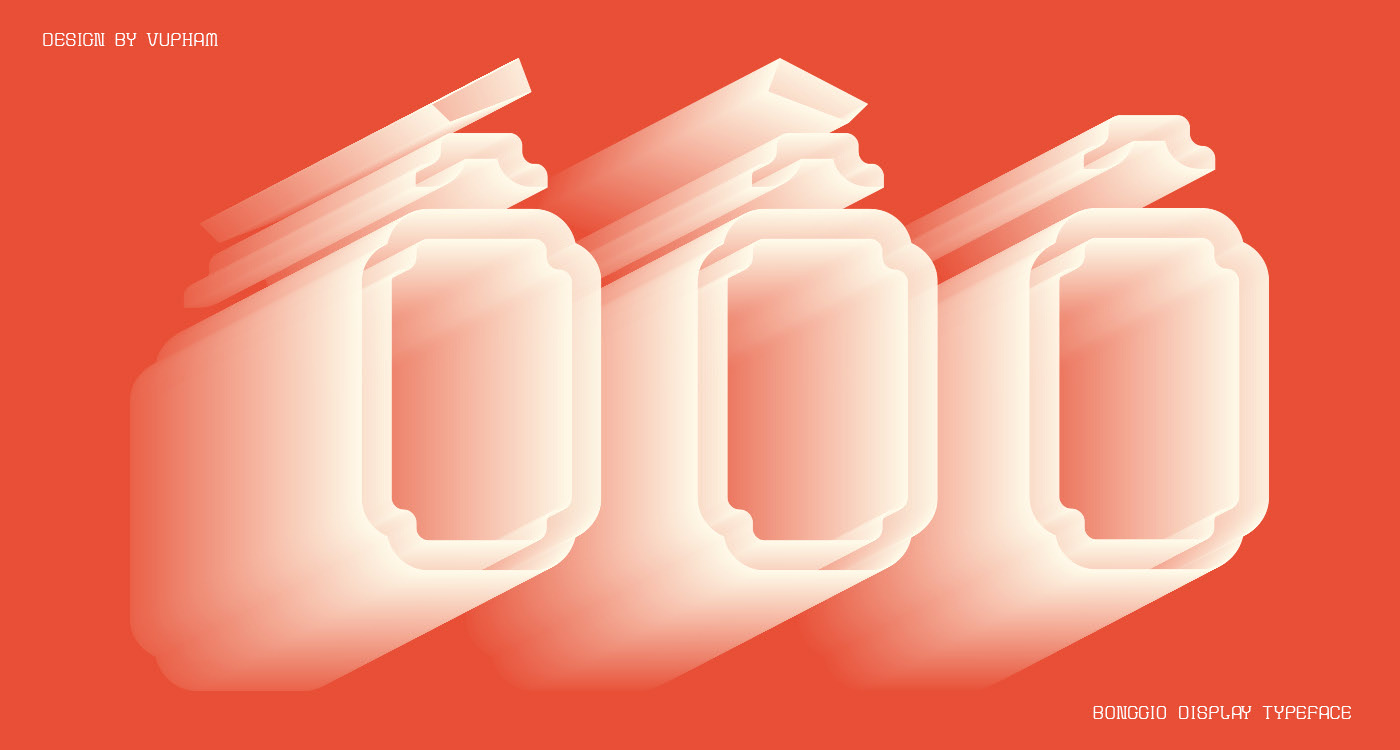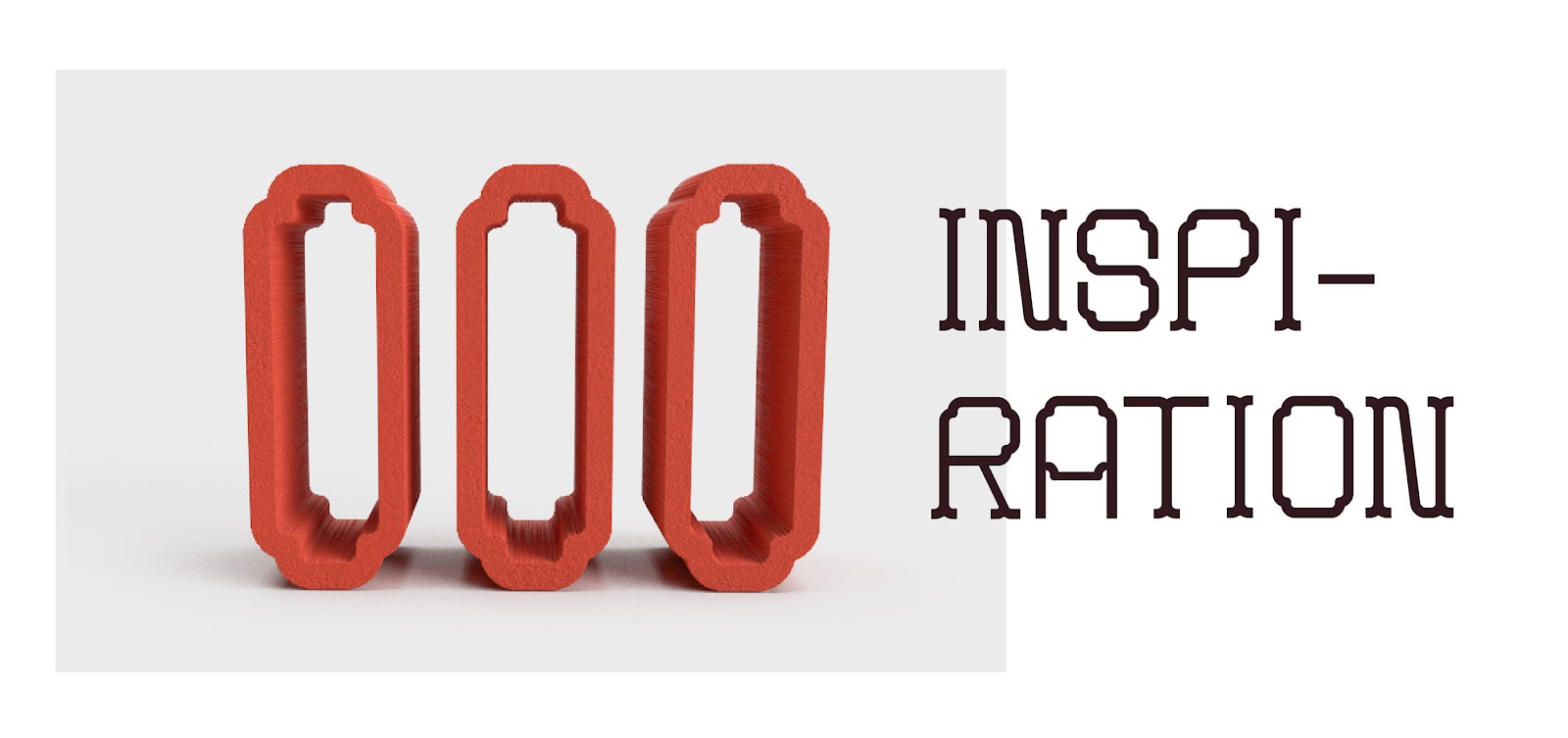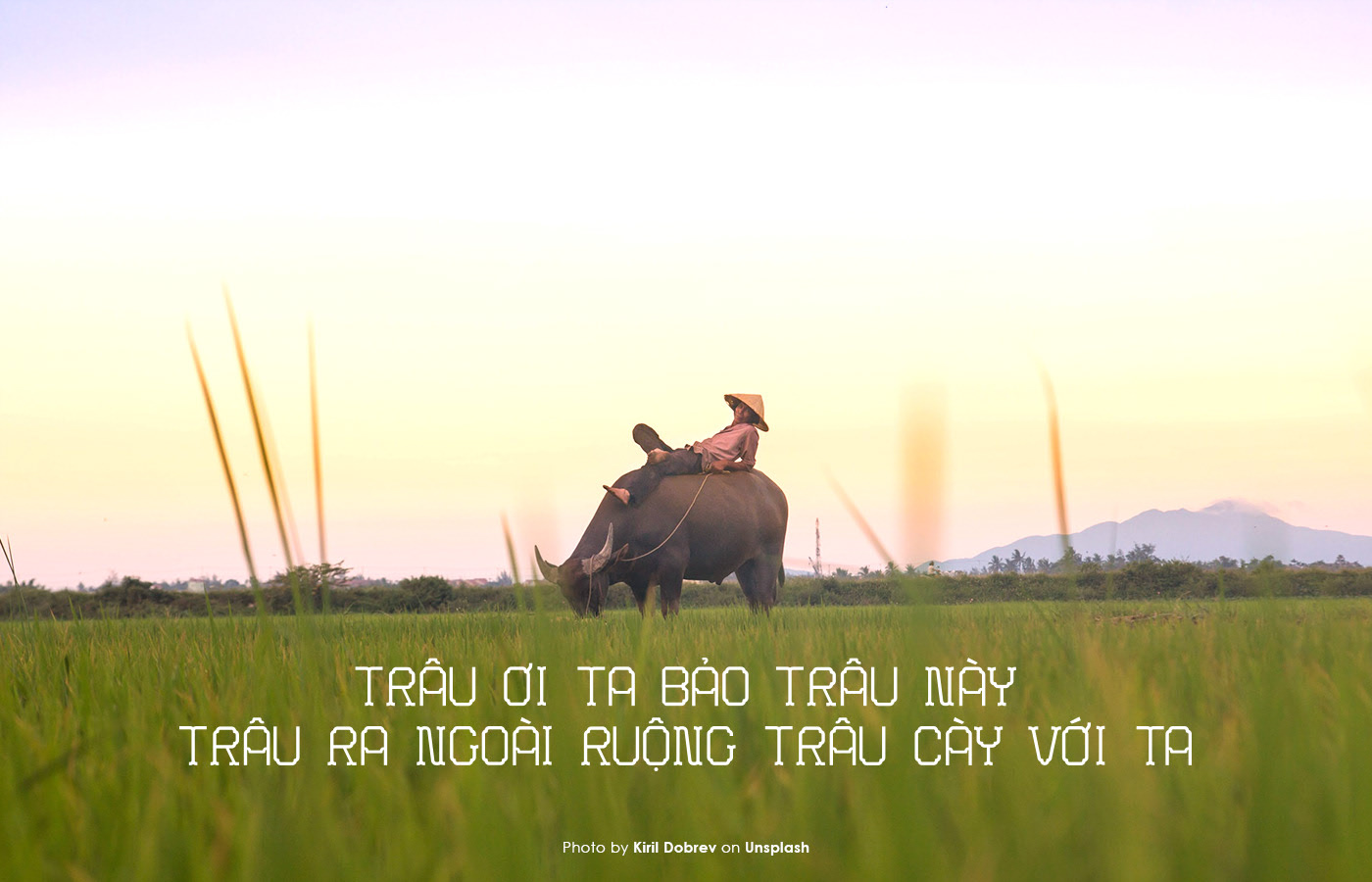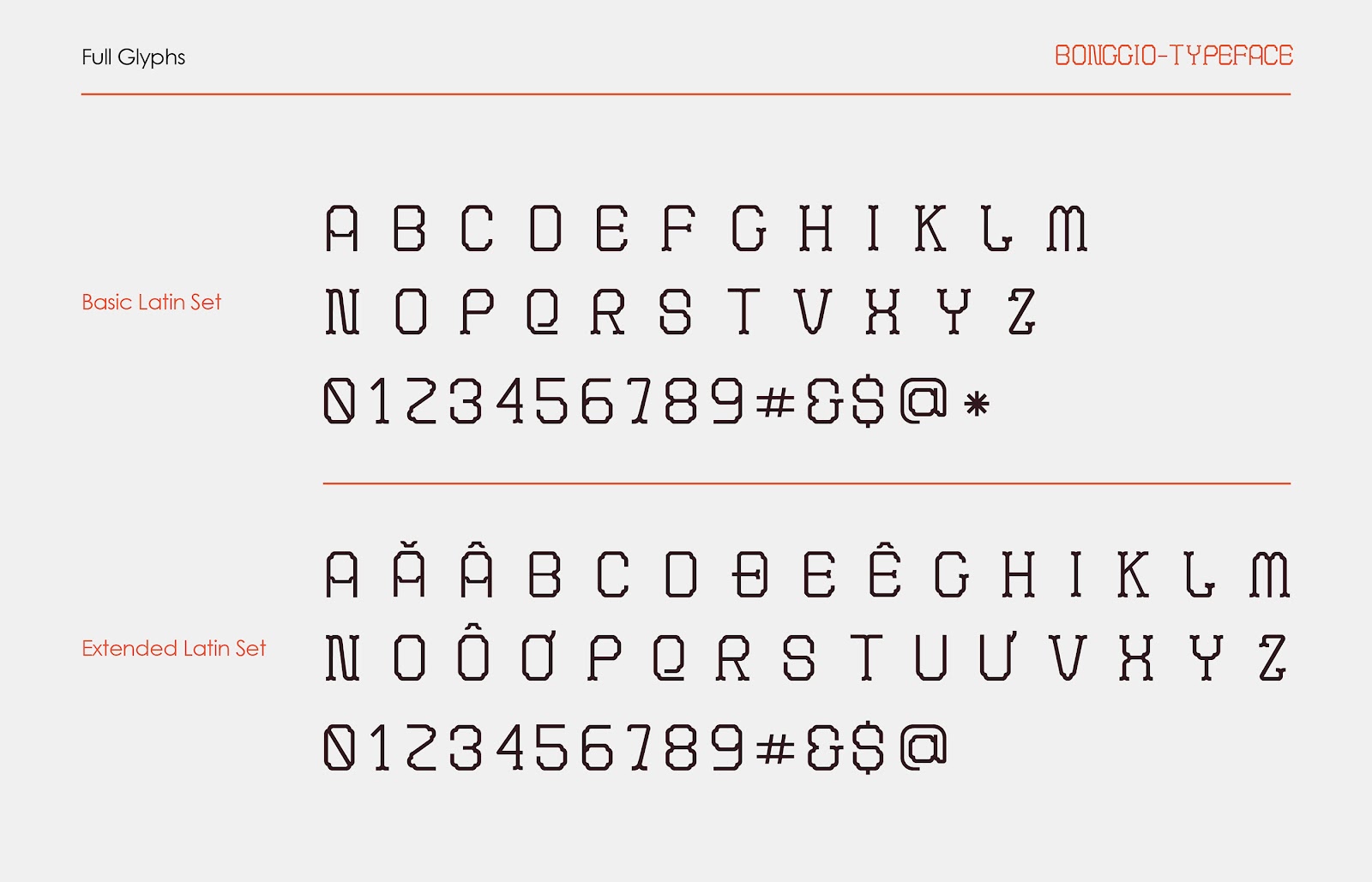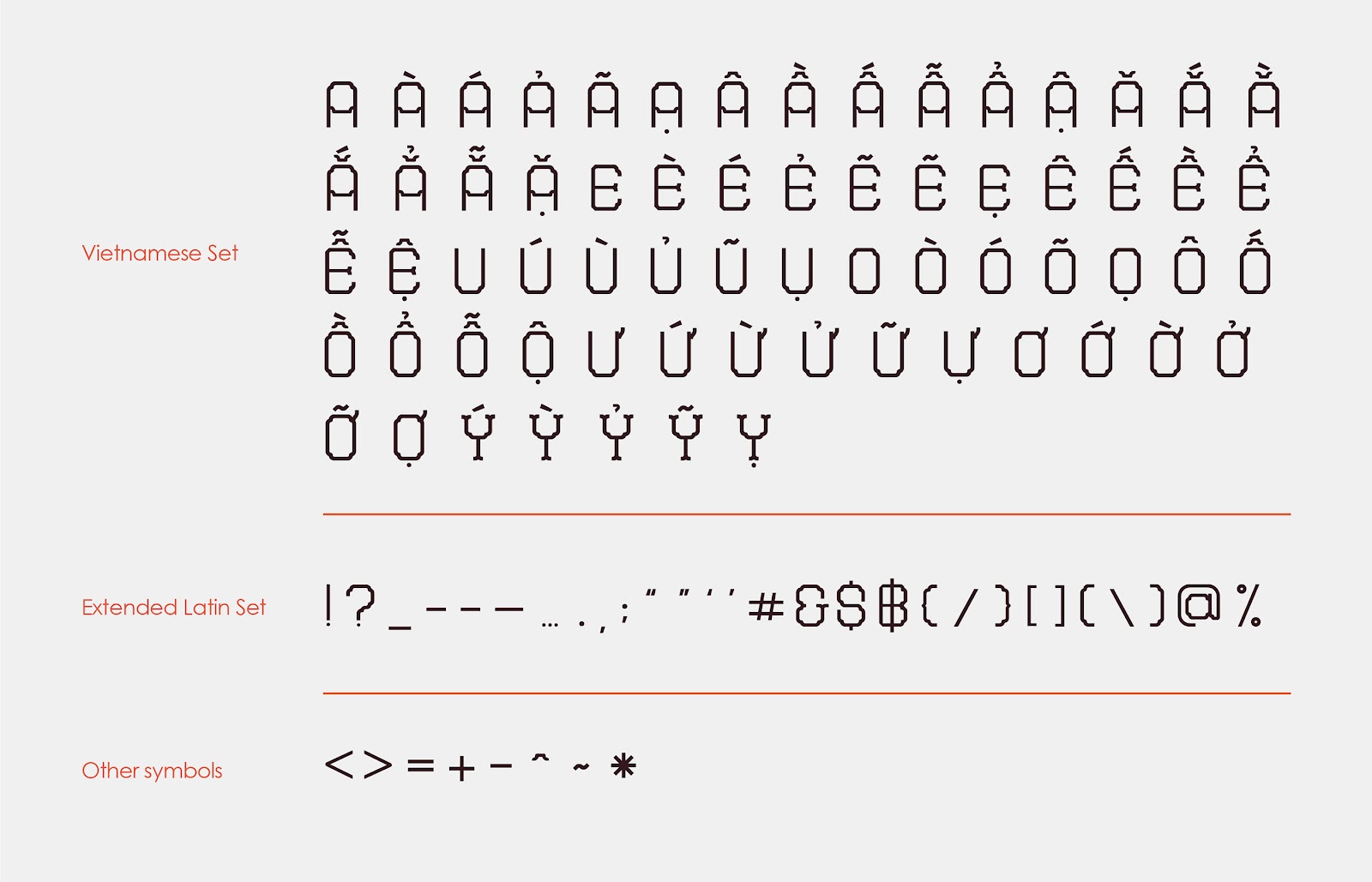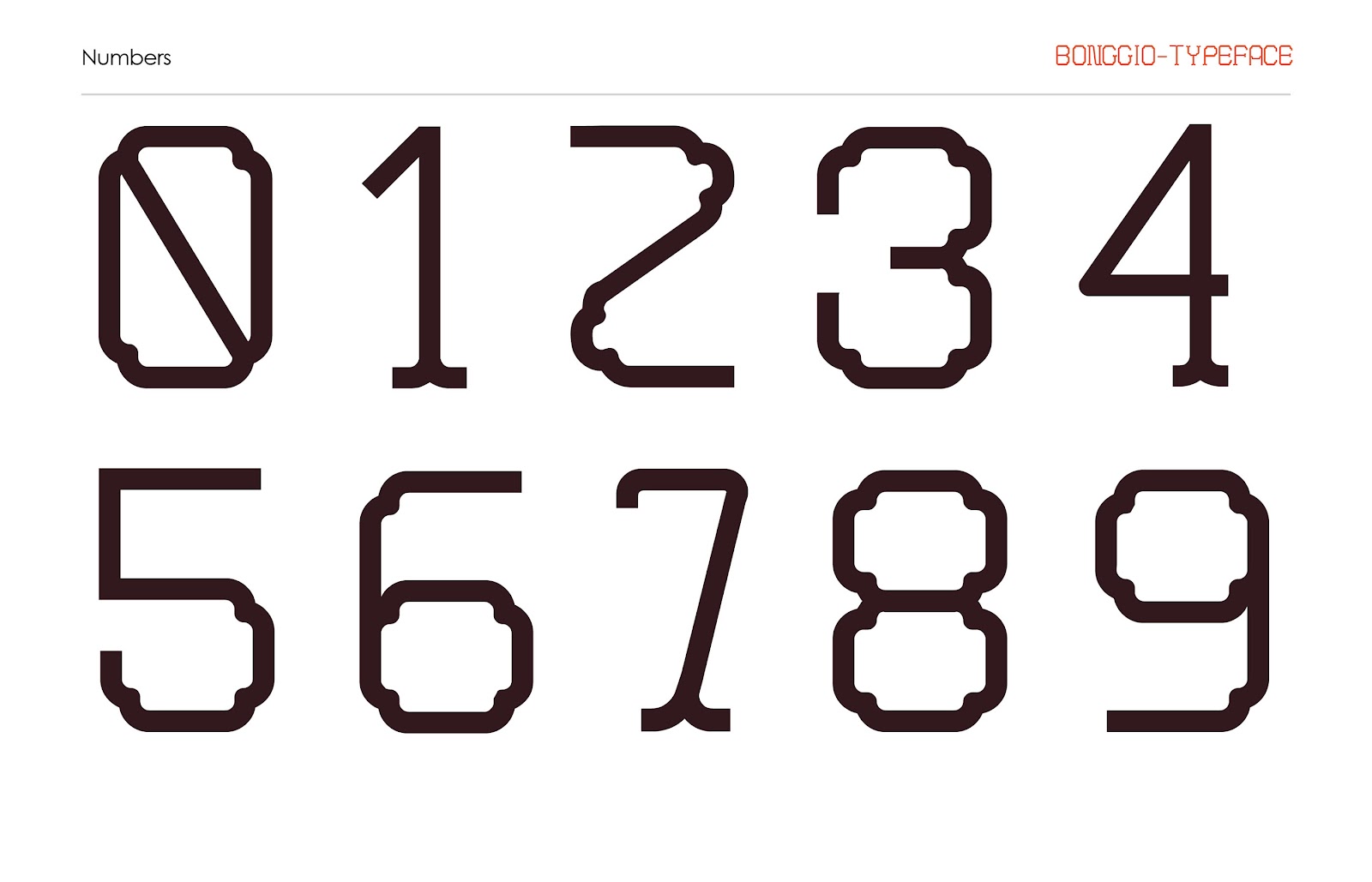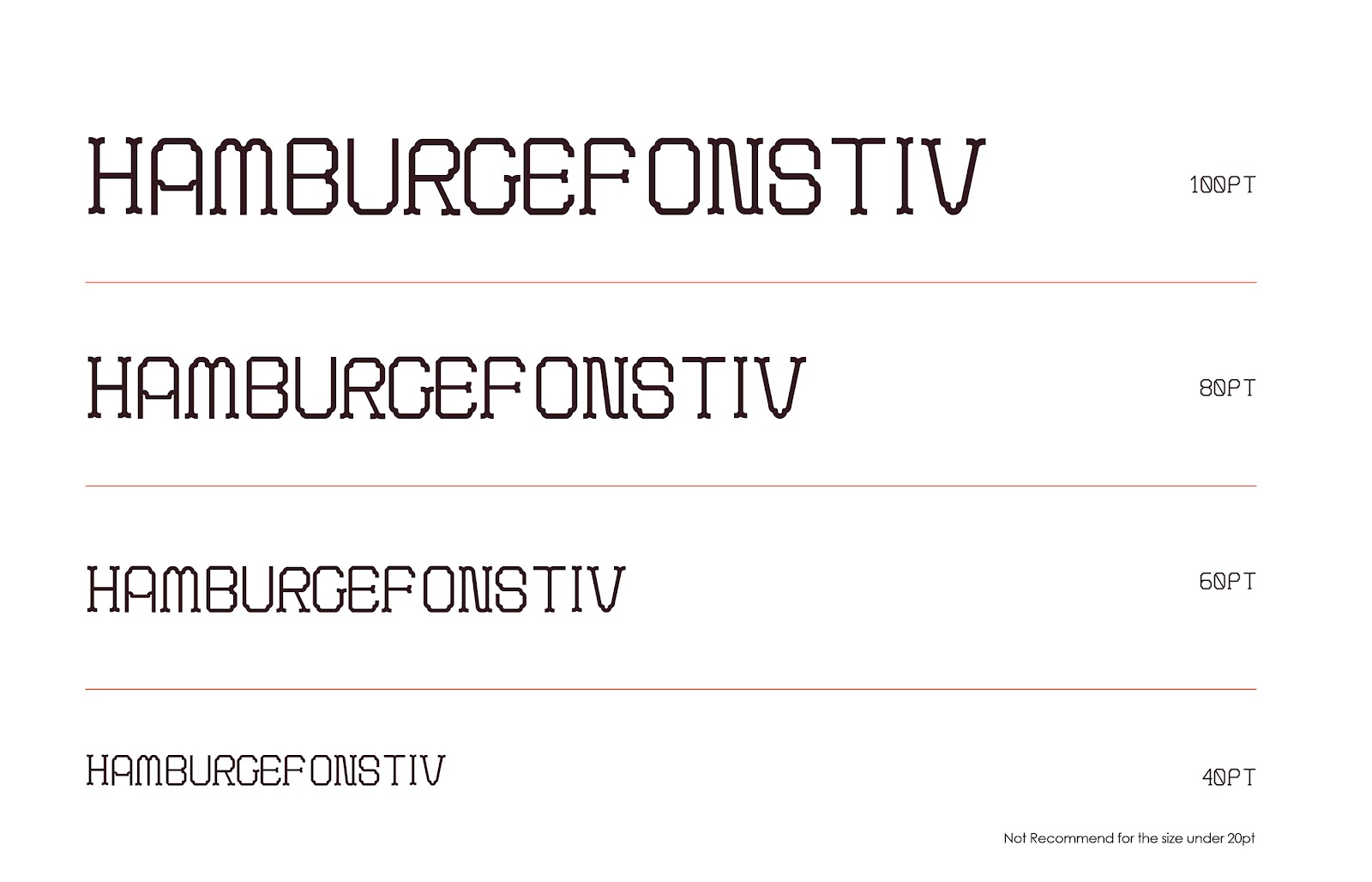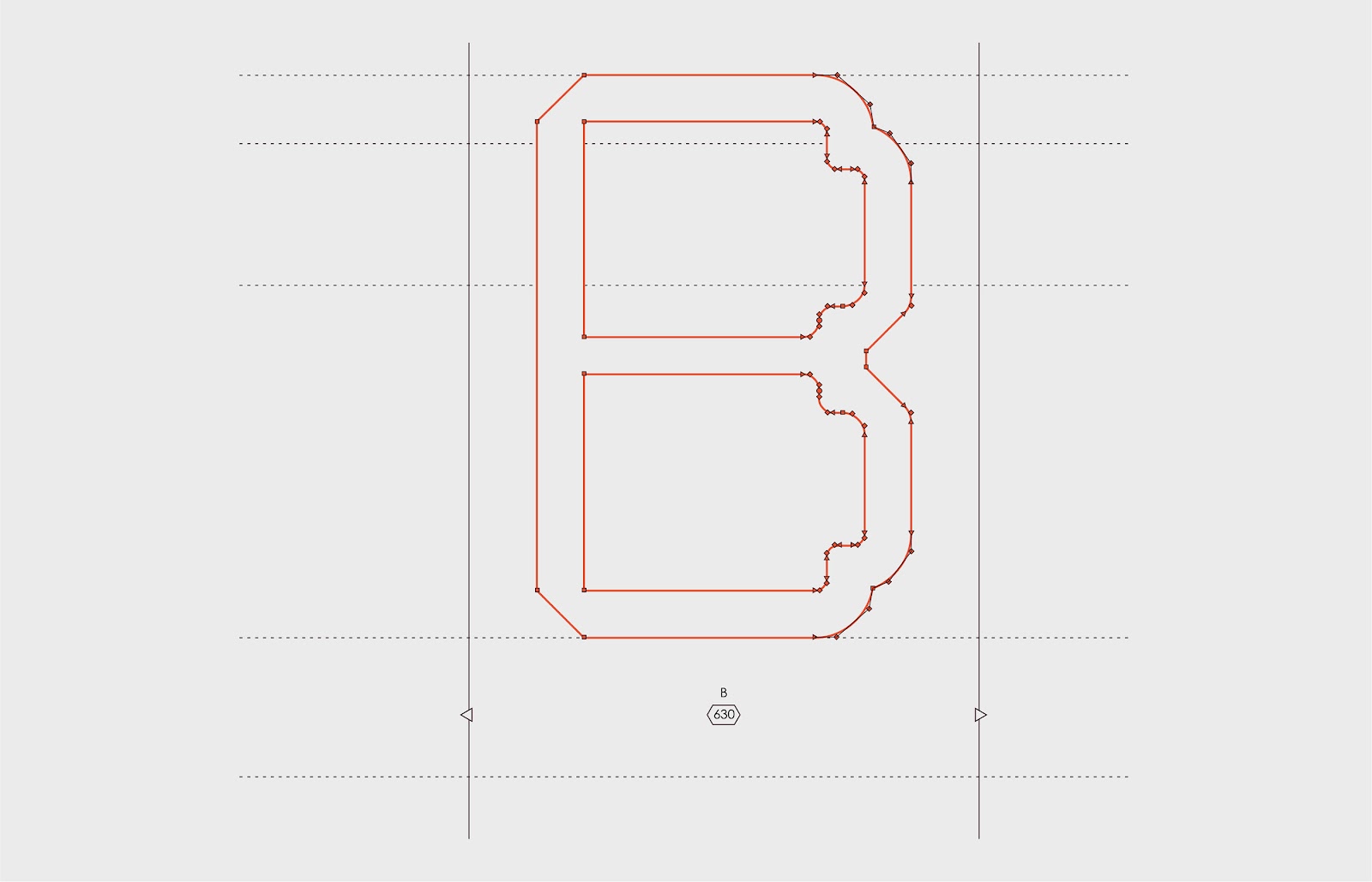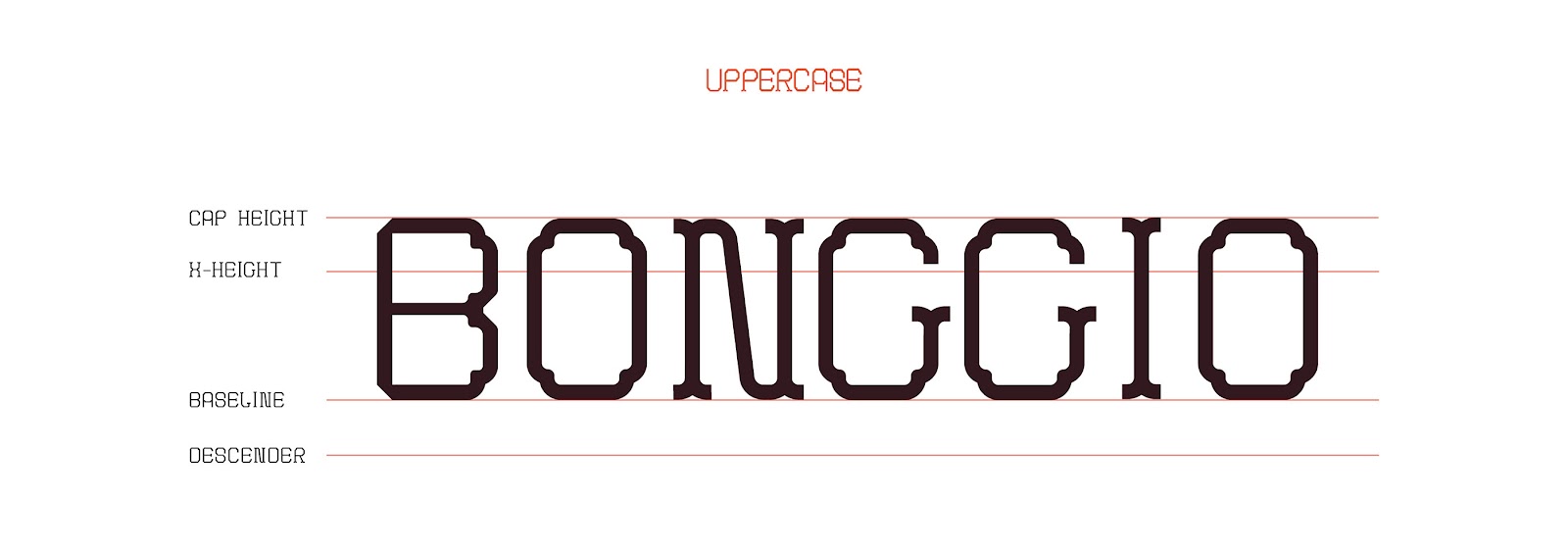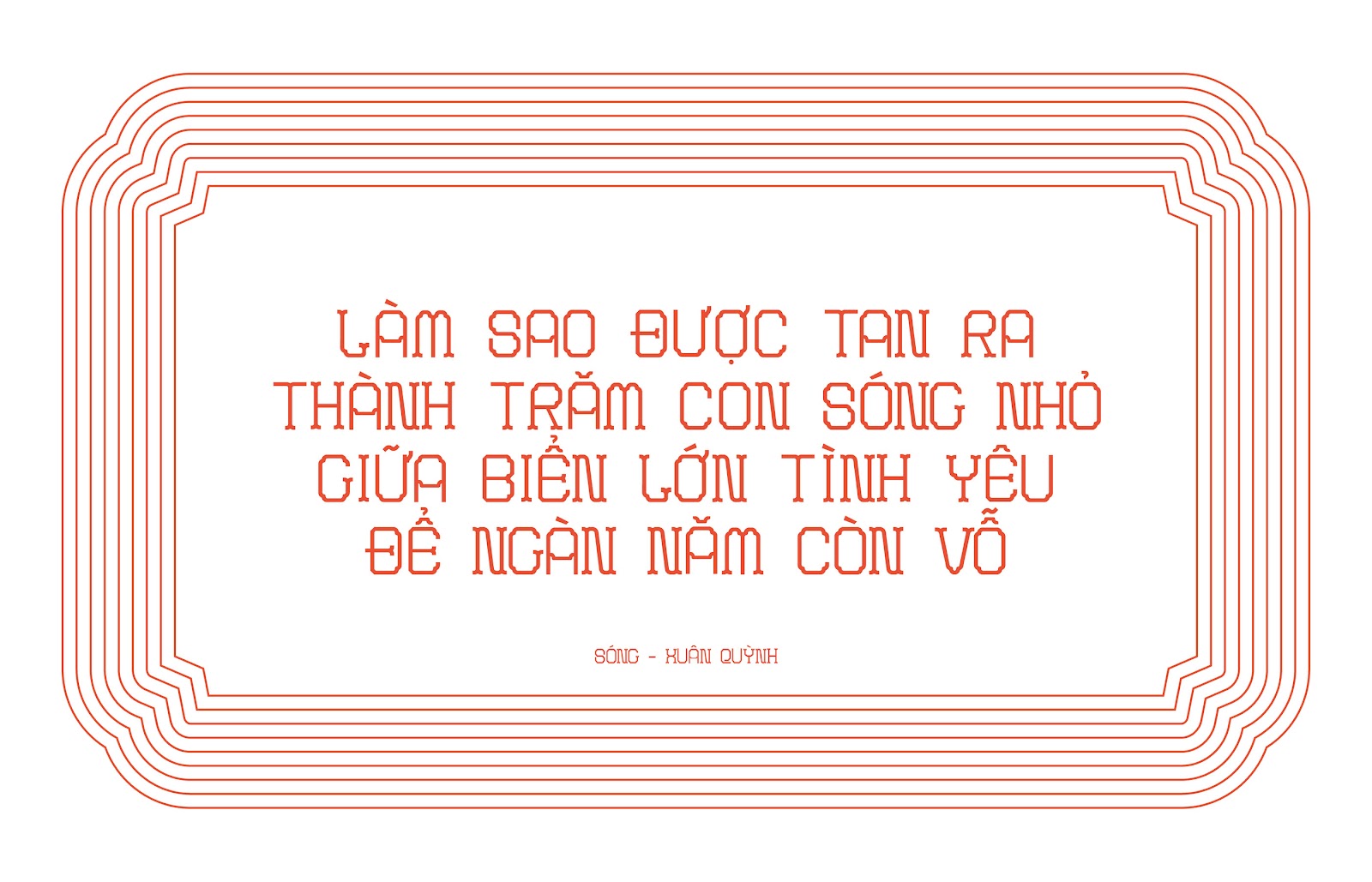
Font Bong Gio – Phông Việt lấm cảm hứng từ gạch Bông Gió
Font Bong Gio được thiết kế bởi Vũ Phạm lấy cảm hứng từ những mẫu gạch Bông Gió phổ biến do người Pháp du nhập vào Việt Nam vào những năm cuối thế kỉ XIX. Kiểu phông chữ Bông Gió mang phong cách cổ điển và truyền thống phù hợp cho rất nhiều các thiết kế khác nhau như các thiết kế xưa cũ và hiện đại.